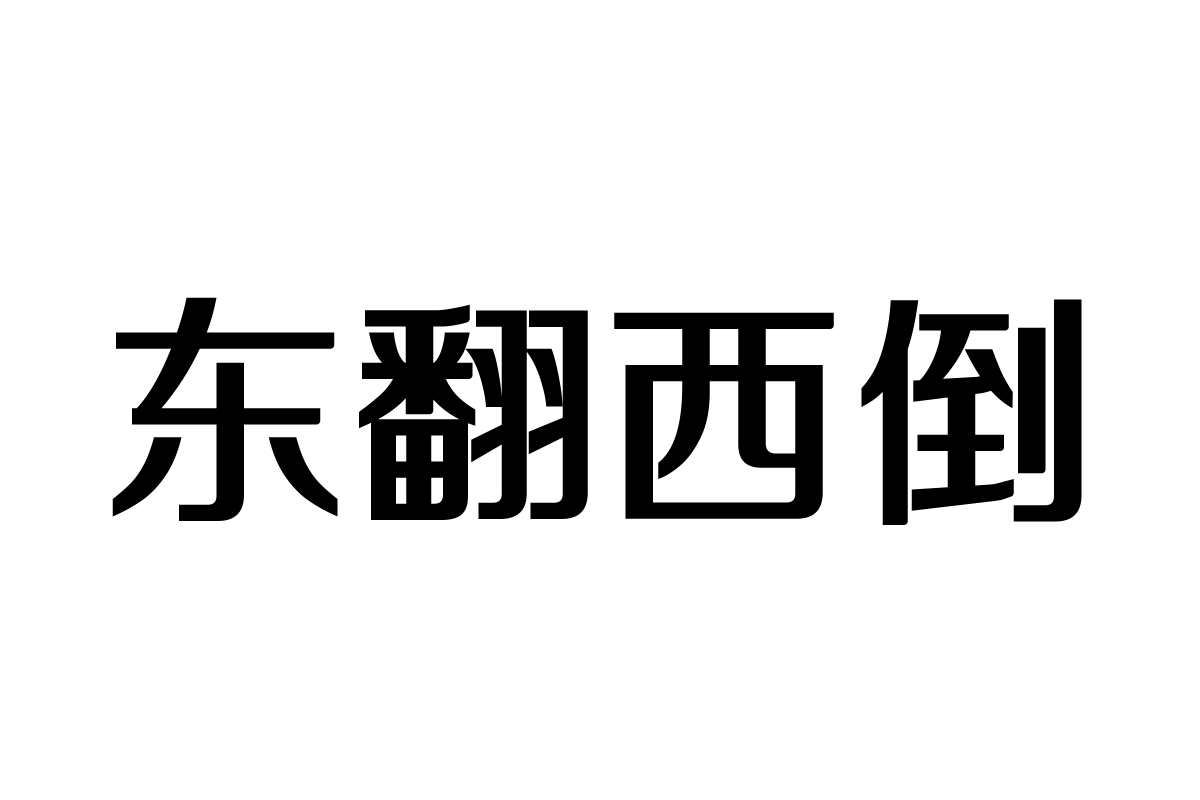
三极正典黑(Sanji Zhengdan Black)是一种无衬线字体,具有简洁、现代的设计风格。它由设计师Sanji Zhengdan于2015年创作,广泛应用于各种品牌标识和广告设计中。
三极正典黑的特点包括:
1. 简洁的线条:该字体的笔画简洁流畅,没有过多的装饰性细节,使得整体视觉效果更加清晰、易读。
2. 现代感:三极正典黑采用了现代的设计元素,如斜体、粗体等,使得字体更加时尚、动感。
3. 可读性强:由于其简洁的线条和现代的设计特点,三极正典黑具有良好的可读性,适用于各种文字排版场景。
4. 适应性强:三极正典黑适用于各种类型的文本排版,无论是标题、正文还是其他信息传递内容,都能保持清晰的视觉效果。
总之,三极正典黑是一款简约而现代的无衬线字体,适用于各种品牌标识和广告设计,具有较高的识别度和吸引力。